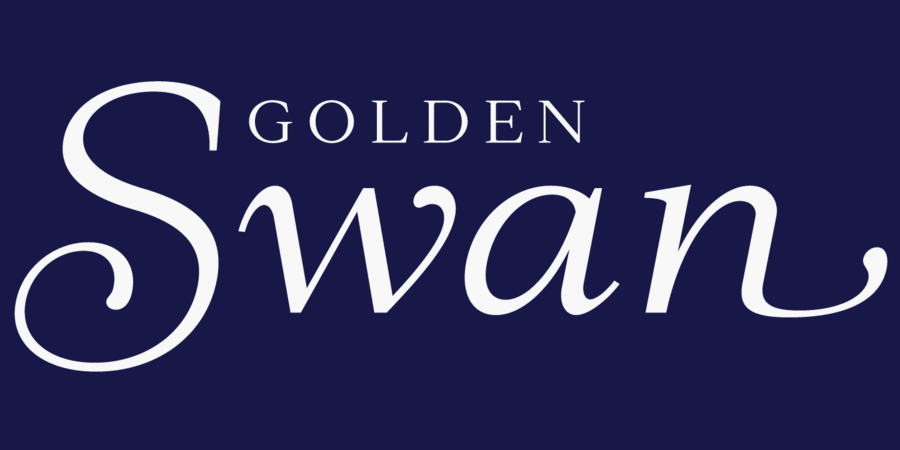
Mantonico – це м'яке й доброзичливе шрифтовое сімейство із зарубками з невеликою висотою рядкових літер. Його злегка широкуваті пропорції та високі виносні елементи створюють своєрідну текстуру, яка підходить для довгого читання. Асортимент накреслень включає 8 насиченостей з відповідними курсивами. Курсив розроблений для додання м'якості, майже текучості. Гарнітура має багату мовну підтримку, включно з кирилицею, та широкий спектр опцій OpenType, таких як капітель, численні набори цифр і понад 300 символів з розчерками. Шрифт розробив Олег Ліщук у 2020 році.